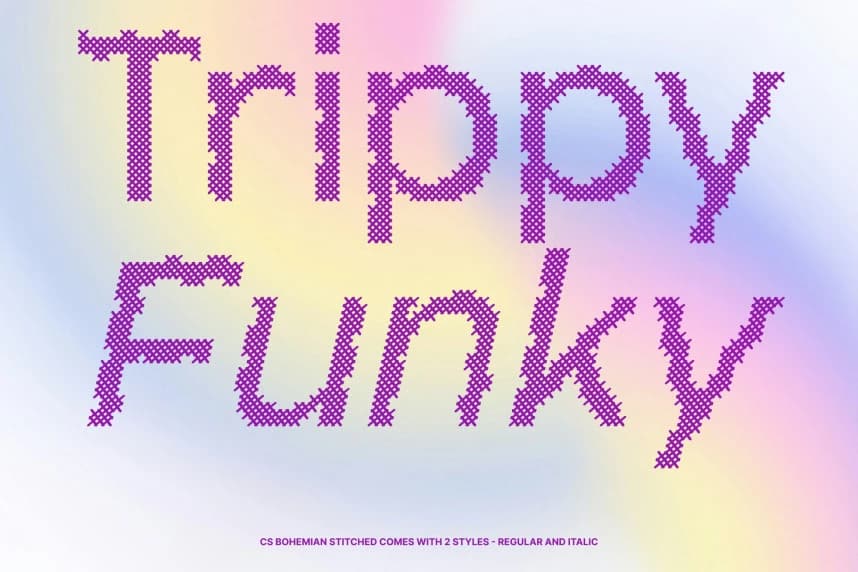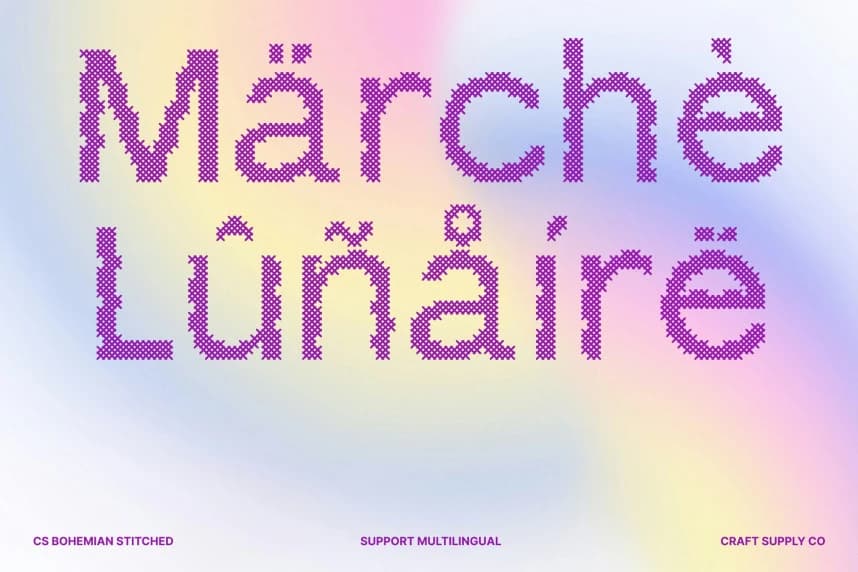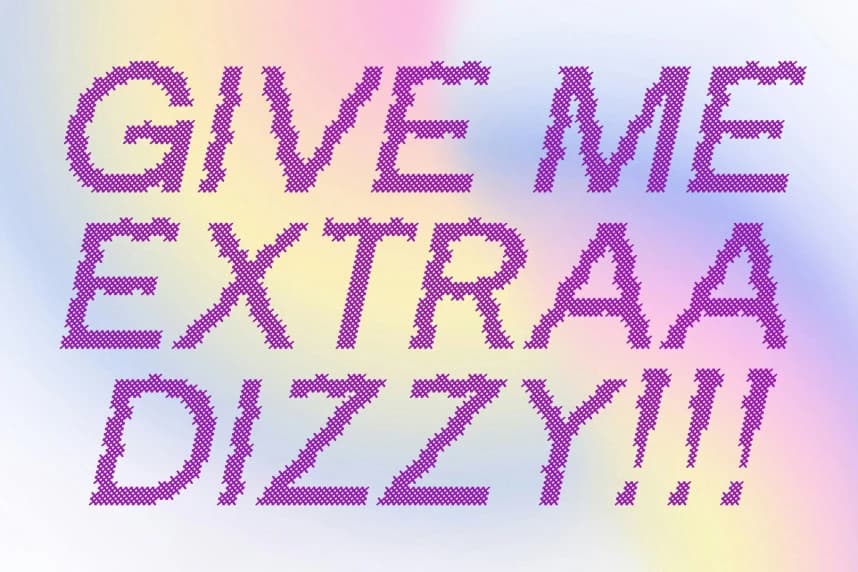
CS Bohemian Dikişli Yazı Tipi
CS Bohemian Stitched Font – El Yapımı Dokuya Sahip Psikedelik Sans-Serif Yazı Tipi; Modern Temiz Stil ile Psikedelik İfadesi Buluşuyor. Bu, zarif çağdaş yapı ile ifade dolu psikedelik biçimleri birleştiren modern bir sans-serif yazı tipidir.
CS Bohemian Stitched Font – El işçiliği dokusuna sahip psikedelik sans-serif fontu. Modern temiz stil psikedelik ifadeyle buluşuyor. Bu, keskin çağdaş yapı ile ifadeli psikedelik formları birleştiren modern bir sans-serif fontudur.